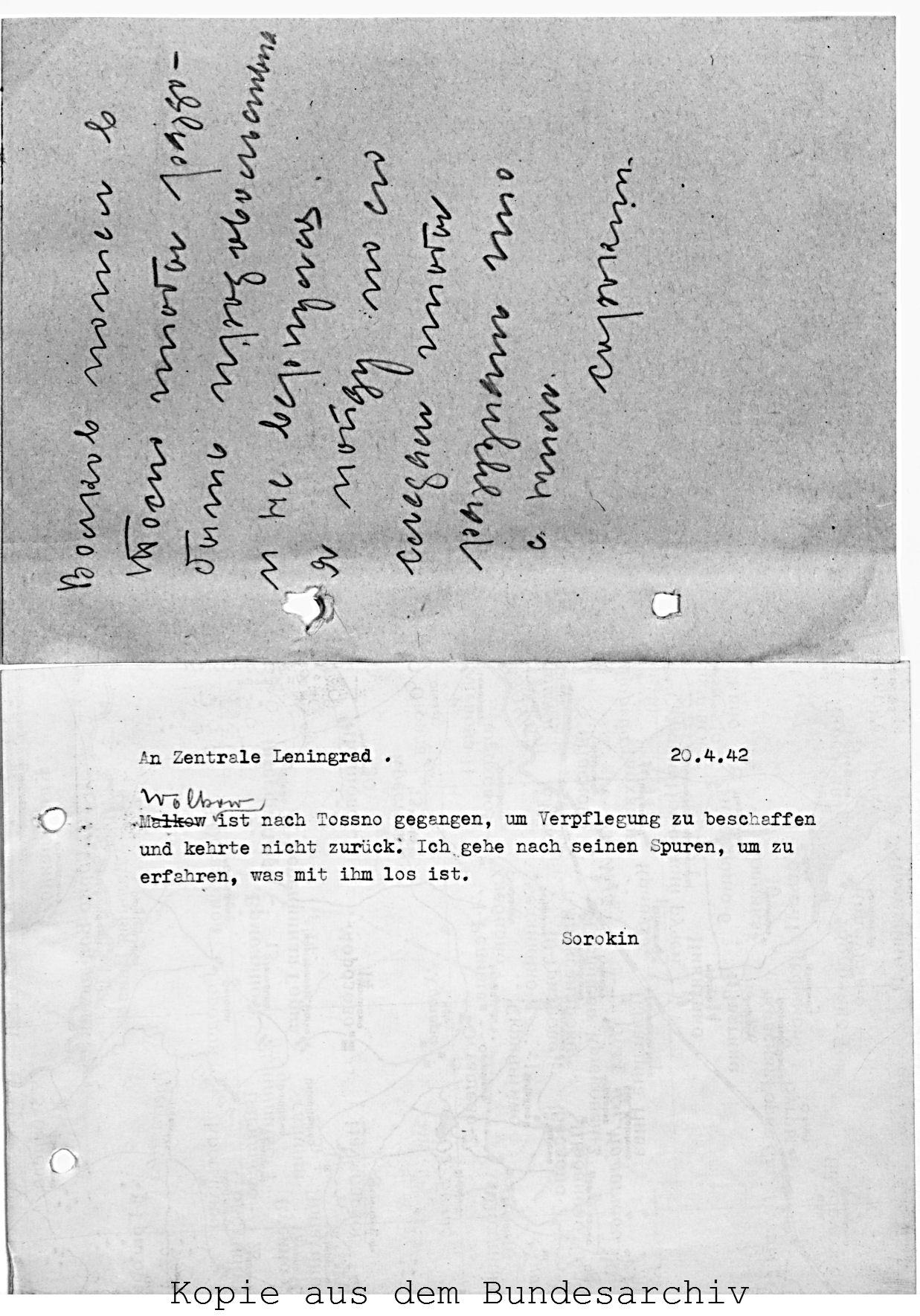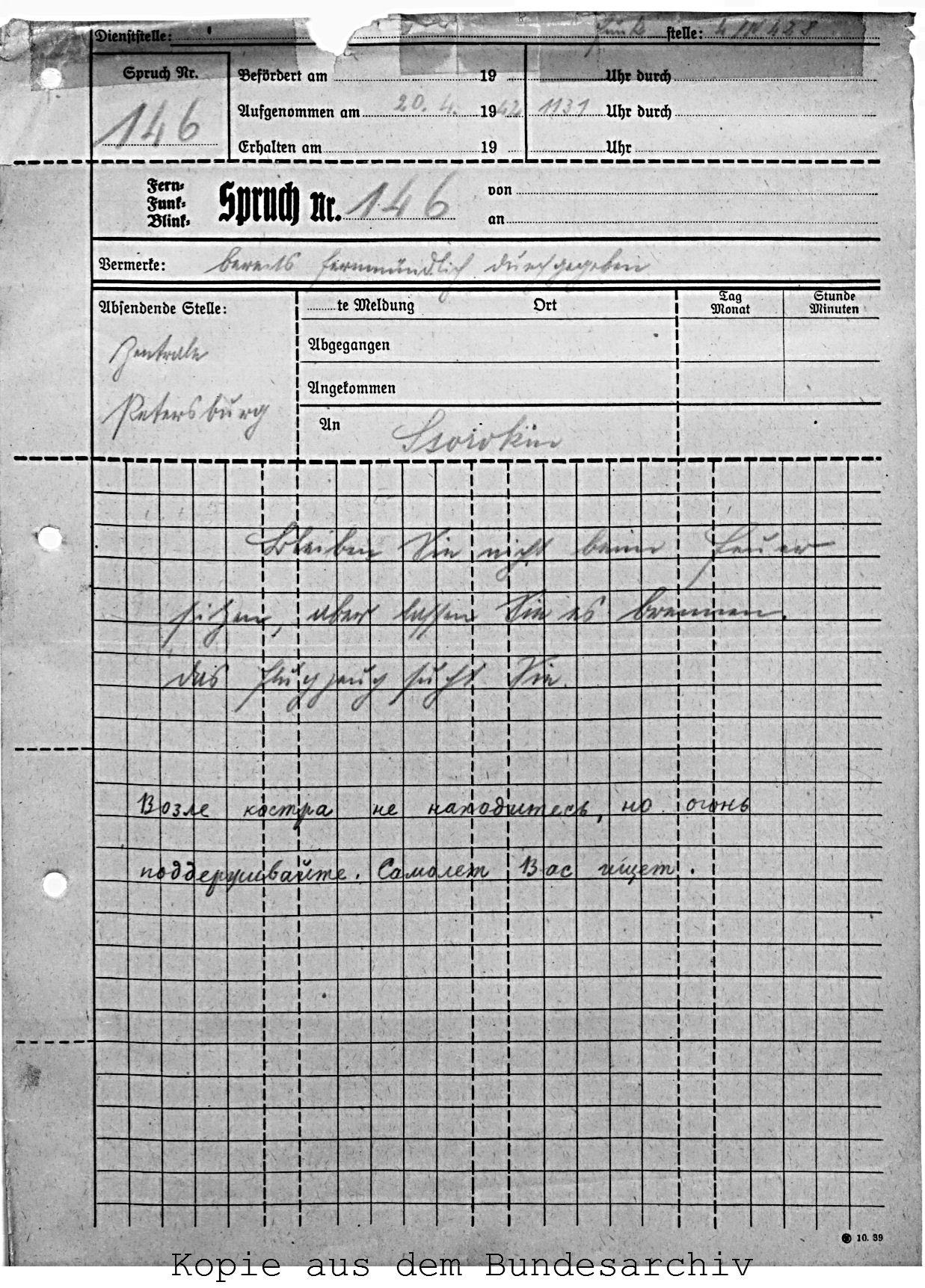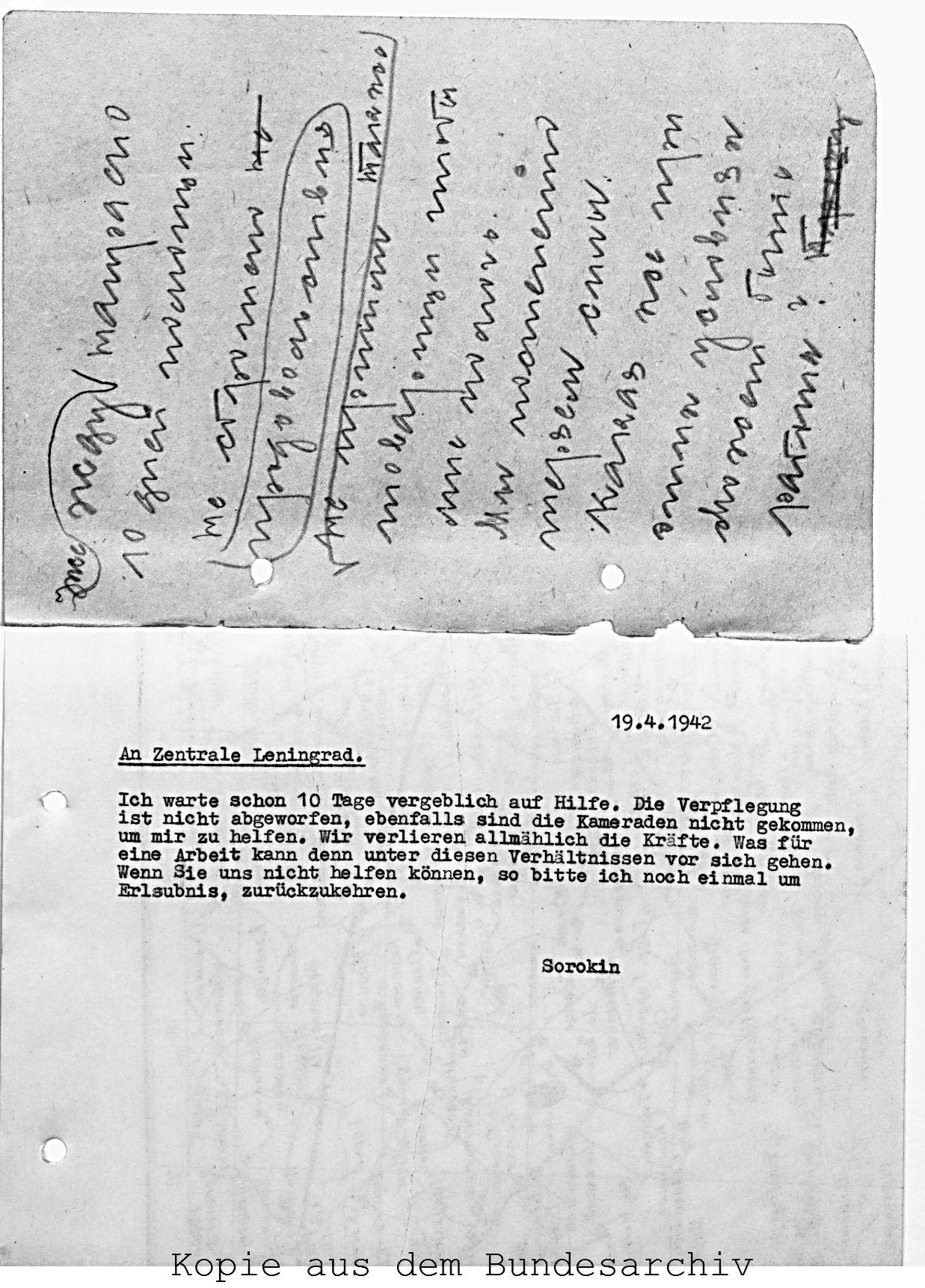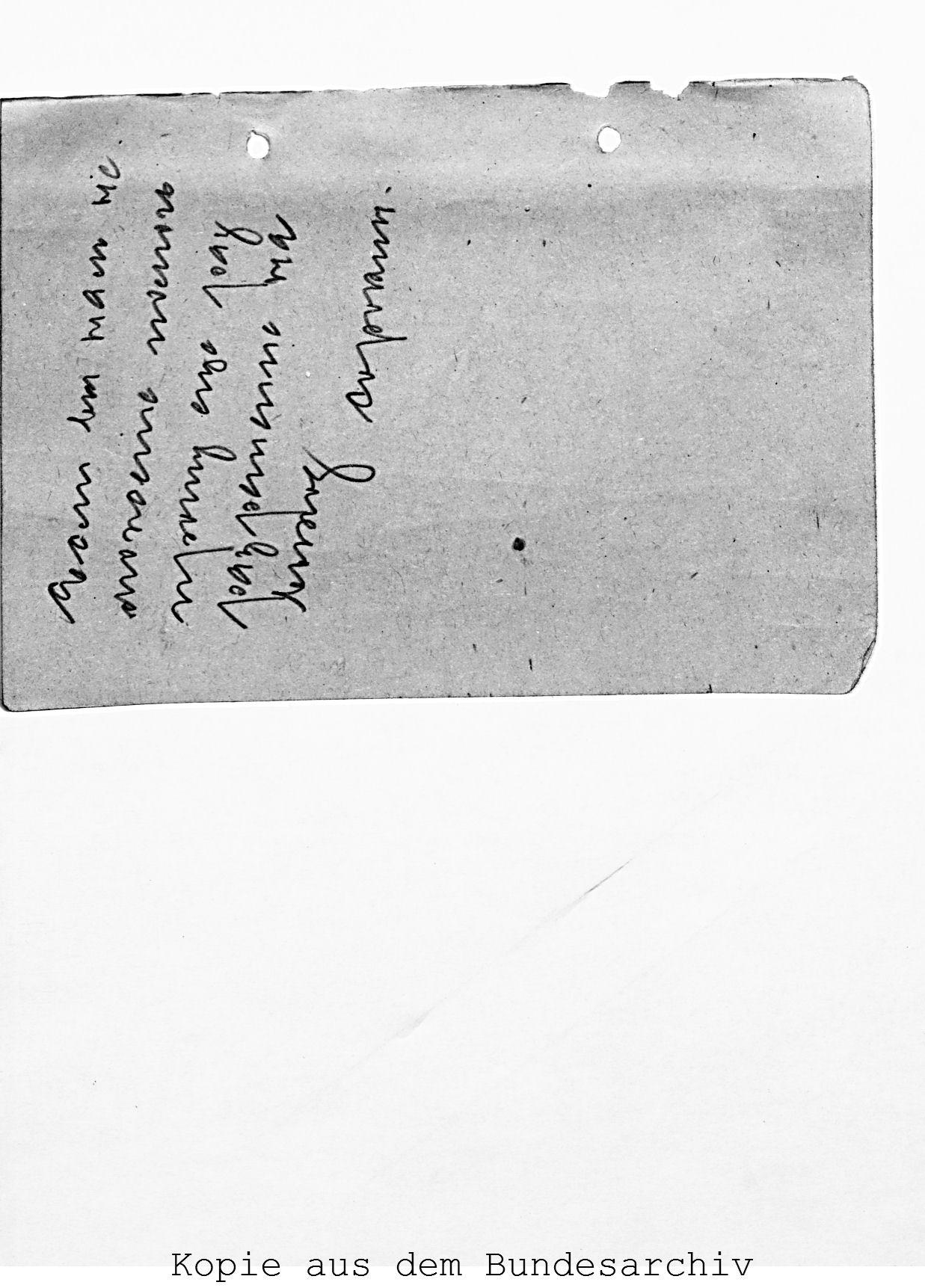
Um welche Schrift handelt es sich hier? (2. Weltkrieg)
kann mir jemand sagen um welche Schrift es sich hierbei handelt? (Ich meine jeweils die Handschriften auf den Dokumenten)
Ich dachte da an Steno oder Sütterlin, vielleicht ist es aber auch russisch?
Bei den Dokumenten handelt es sich um Funkverkehr aus dem 2. Weltkrieg.
Wird das nicht aus dem Kontext klar? Das ist russische Schreibschrift. Die mit "Sorokin" unterschriebene eher etwas unleserlich geschrieben, die mit "Major" unterschriebenen  erinnert sehr an die von mir in der Schule erlernte Schreibschrift. Dazu jeweils die deutsche Übersetzung.
Und an den Stellen, wo die deutsche Übersetzung von Hand geschrieben und nicht mit der Schreibmaschine getippt wurde, handelt es sich um sog. Kurrentschrift, also die zu dieser Zeit übliche Handschrift. Auf den Blättern mit "Spruch Nr." ist in der Regel zunächst die deutsche Version in deutscher (Kurrent-)Schreibschrift, danach die russische Version in russischer Schreibschrift aufgeführt.
Und Kurrent-Schrift ist eben die erwachsenen-Handschrift, welche diese Leute als Kinder mit Hilfe der Schul-Schreibschrft von Ludwig Sütterlin erlernt haben. Diese wird vielfach dann auch Sütterlin genannt, was eigentlich falsch ist, denn das ist eigentlich für die Kinderhand, die noch schlecht aus dem Handgelenk geschrieben werden konnte sehr aufrecht geformte Schüler-Lernschrift.